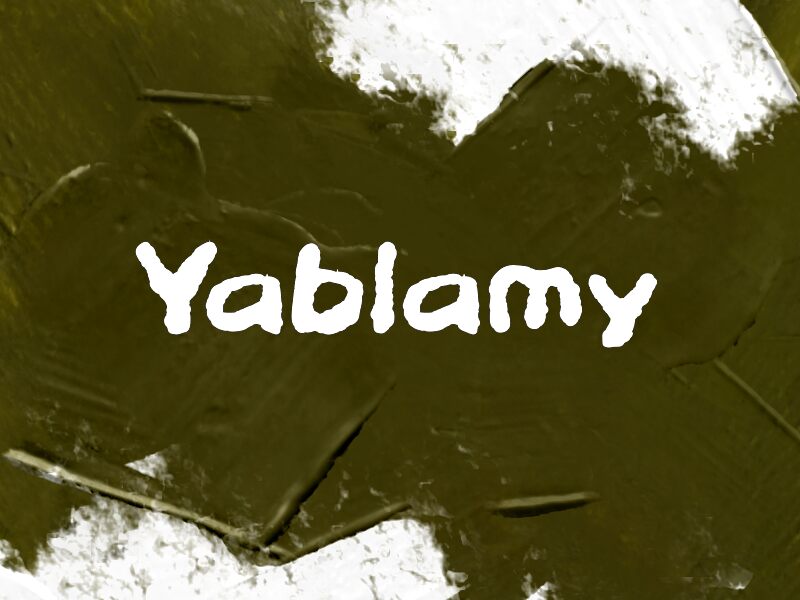
Yablamy
Yablamy da Wep é uma fonte gratuita de estilo pincel, marcada por traços volumosos e bordas irregulares que fazem com que as letras pareçam carimbadas em vez de desenhadas. Esse ritmo desigual e levemente irregular confere ao design uma presença artesanal, com formas suaves e arredondadas que mantêm o estilo descontraído, sem agressividade.
É a escolha ideal para títulos de pôsteres, menus de café, rótulos de embalagens, gráficos para redes sociais e flyers de eventos, onde a textura de pincel já traz todo o estilo necessário. Títulos curtos e logotipos beneficiam-se especialmente do seu contorno borrado, que dá às palavras um toque casual e pintado à mão.